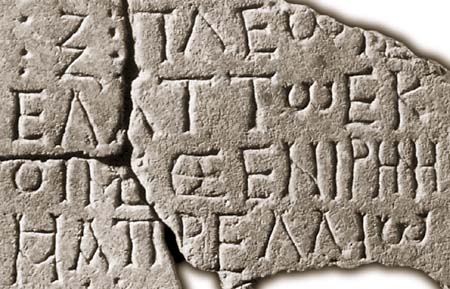
As letras dos Gregos, 2Na geografia portuguesa, a letra grega aparece apenas no contexto da cultura paleocristã, de cunho bizantinico.
Paleocristão é um termo que não designa um estilo, antes se refere a qualquer obra de arte executada por ou para cristãos nos primeiros cinco séculos da nossa era. É a partir do século IV que a arte cristã se divulga na Península. Entre nós, só a partir do século VI são edificados templos paleocristãos que, pelas suas dimensões, complexidades de plantas e qualidade do aparelho, revelam a importância do território. Entre eles são dignos de destaque Mértola, Torre de Palma e Dume. Mértola - Basílica Paleocristã. O «Núcleo visigótico» do Museu de Mértola foi instalado no espaço de uma Basílica Paleocristã para dar a conhecer o período da primeira cristianização do Sul de Portugal. O núcleo expõe estruturas arquitectónicas e cerca de 30 lápides oriundas do cemitério alto-medieval de Mértola. Apesar da concentração de vestígios romanos na vila de Mértola (Criptopórtico, Torre Couraça, casa romana e vias romanas), podem também encontrar-se vestígios de menor dimensão em todo o Concelho. Com a adopção do Cristianismo pelos romanos, os cidadãos de Mértola acompanharam os sinais de mudança, facto testemunhado pelos vestígios arqueológicos representativos de locais de culto e enterramento na cidade (basílicas Paleocristãs do Rossio do Carmo e da Alcáçova onde se observa um baptistério octogonal). São Martinho esteve directamente ligado à construção de um templo em Dume, perto de Braga, mandado erigir por Chararicus, rei dos Suevos. Segundo C.A.Ferreira de Almeida e de acordo com as escavações ainda em curso, trata-se de um mausoléu de planta centralizada, construído para albergar relíquias de santos, neste caso Martinho de Tours. O próprio São Martinho terá participado na escolha da planta que seguiria o modelo oriental de cabeceira trilobada. Temas relacionados